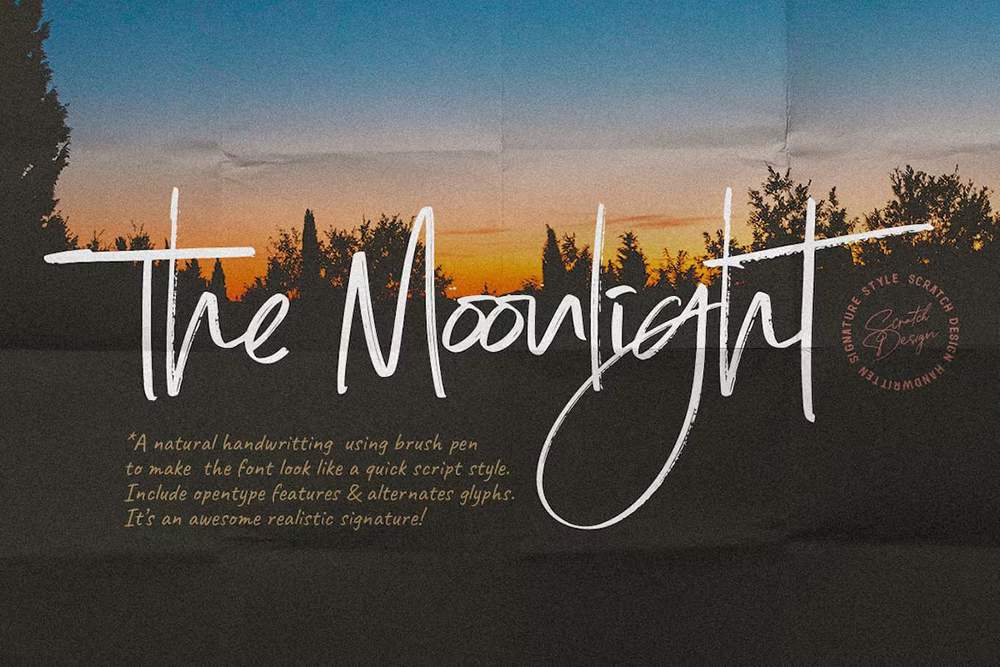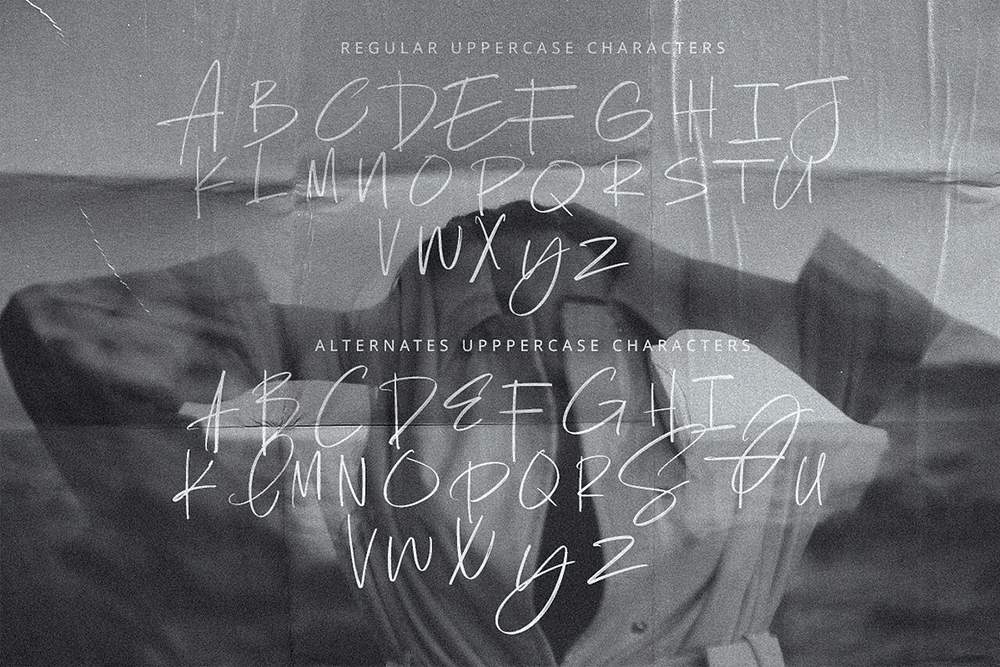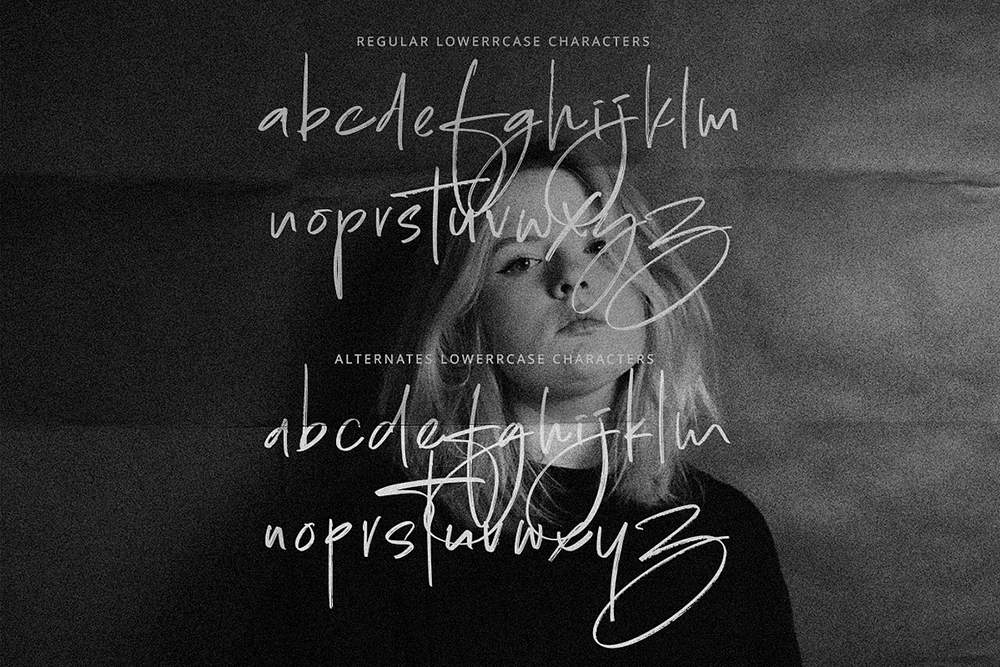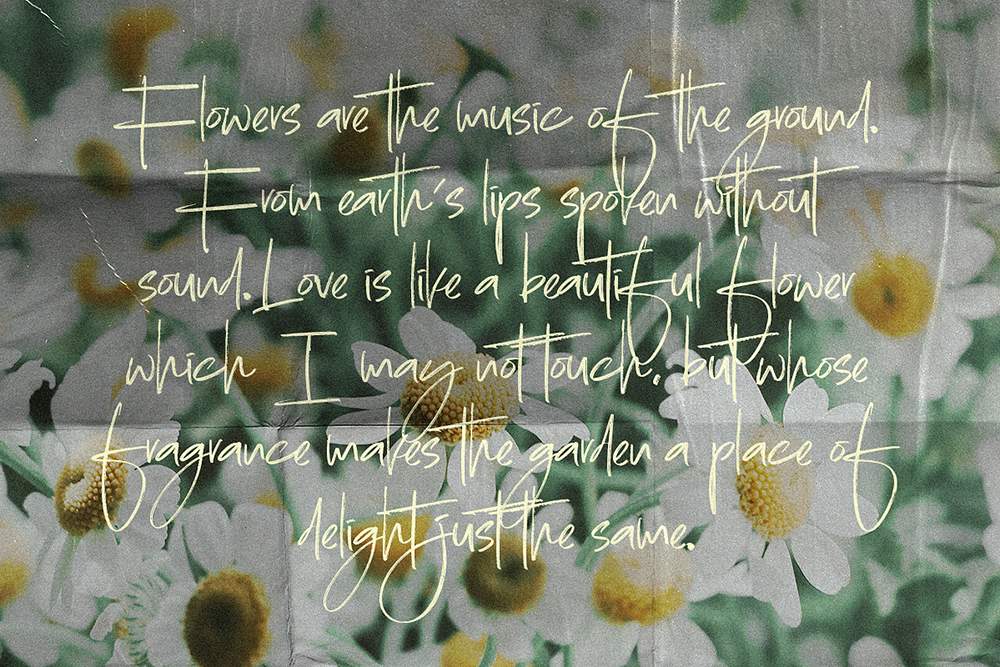
فونت پرمیوم و انگلیسی Moonlight Font یک فونت دستخط طبیعی و مدرن با سبک خاص و بافت قلمو است و در دو سبک با گزینههای جایگزین میباشد. فونت Moonlight از چند زبان، Swashes و Alternate و Ligature پشتیبانی میکند که میتوانید آن را در حالت Open Type در فتوشاپ و… اعمال کنید.
مزایای استفاده از فونت لاتین Moonlight چیست؟